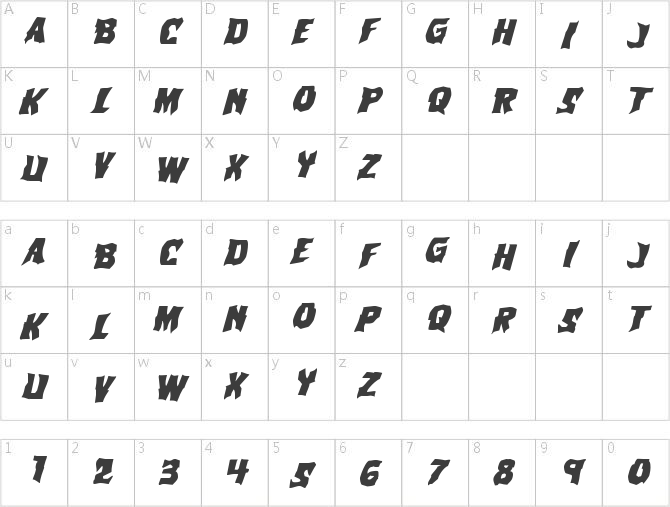
Vorvolaka Expanded Italic
Vorvolaka Expanded Italic介紹
Vorvolaka Expanded Italic字體字庫是一款讓人賞心悅目、百看不厭的英文字體,適合各類廣告和產品包裝設計應用,字體大小0.06MB,格式為ttf字體,上傳用戶是漫步云端,作者/版權方為未知